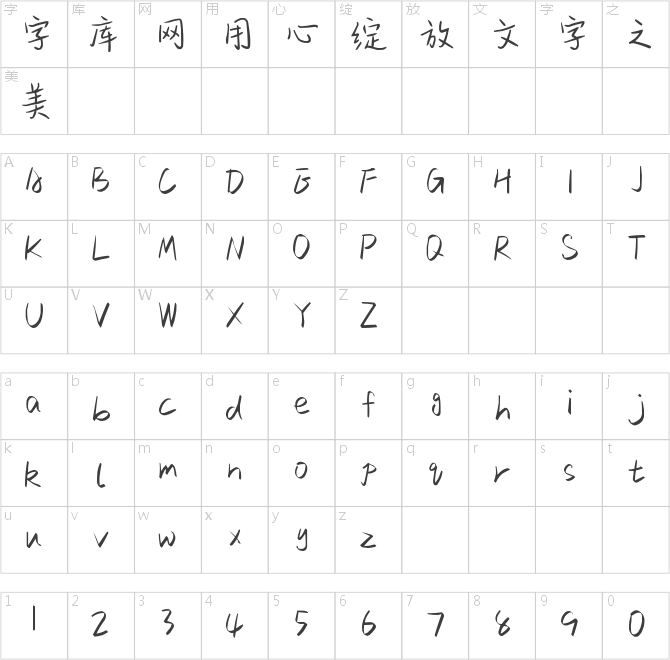
想你時(shí)最快樂(lè)
想你時(shí)最快樂(lè)是一款風(fēng)格獨(dú)特的手寫體。該字體整體瘦高,視覺(jué)向右上傾斜,筆畫上橫畫左低右高。該字體適用于文藝類的書刊、品牌廣告和產(chǎn)品包裝設(shè)計(jì),以及社交網(wǎng)絡(luò)的個(gè)性化用字。
想你時(shí)最快樂(lè)字體FZSJ-XIANGNSZKL字庫(kù)是一款讓人賞心悅目、百看不厭的中文字體,適合各類廣告和產(chǎn)品包裝設(shè)計(jì)應(yīng)用,字體大小3.22MB,格式為TTF字體,上傳用戶是釜源貿(mào)易,作者/版權(quán)方為方正手跡/俞亦婷